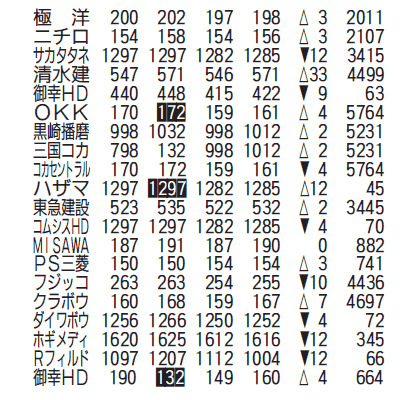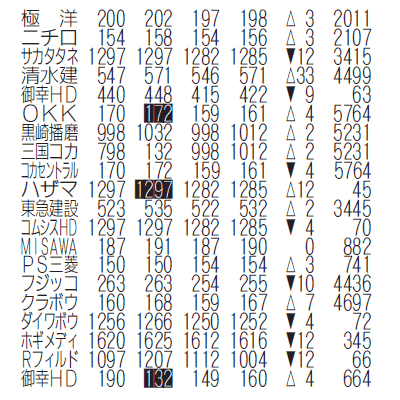
イワタU-PRESSver2の紹介(2005年2月)
イワタU-PRESSは下記文字を追加し、Ver.2.1にバージョンアップしました。
これにより内字15269,外字848の合計16117字となりました。
新書体情報
新聞中ゴシック体,新聞中ゴシック体新がな
新聞ゴシック体と新聞中太ゴシック体の中間ウェイトの書体です。
新聞明朝体と組み合わせてお使いいただくこと想定して開発しました。
新がなと旧がなの2書体を用意しています。
商況用フォント
現在RとLの2種類のウェイトを用意しています。
それぞれ銘柄文字、数字、ネガ数字、記号類など、見やすく配慮したデザインとなっています。
| イワタ株式ゴシック体 R |
| イワタ株式ゴシック体 L |